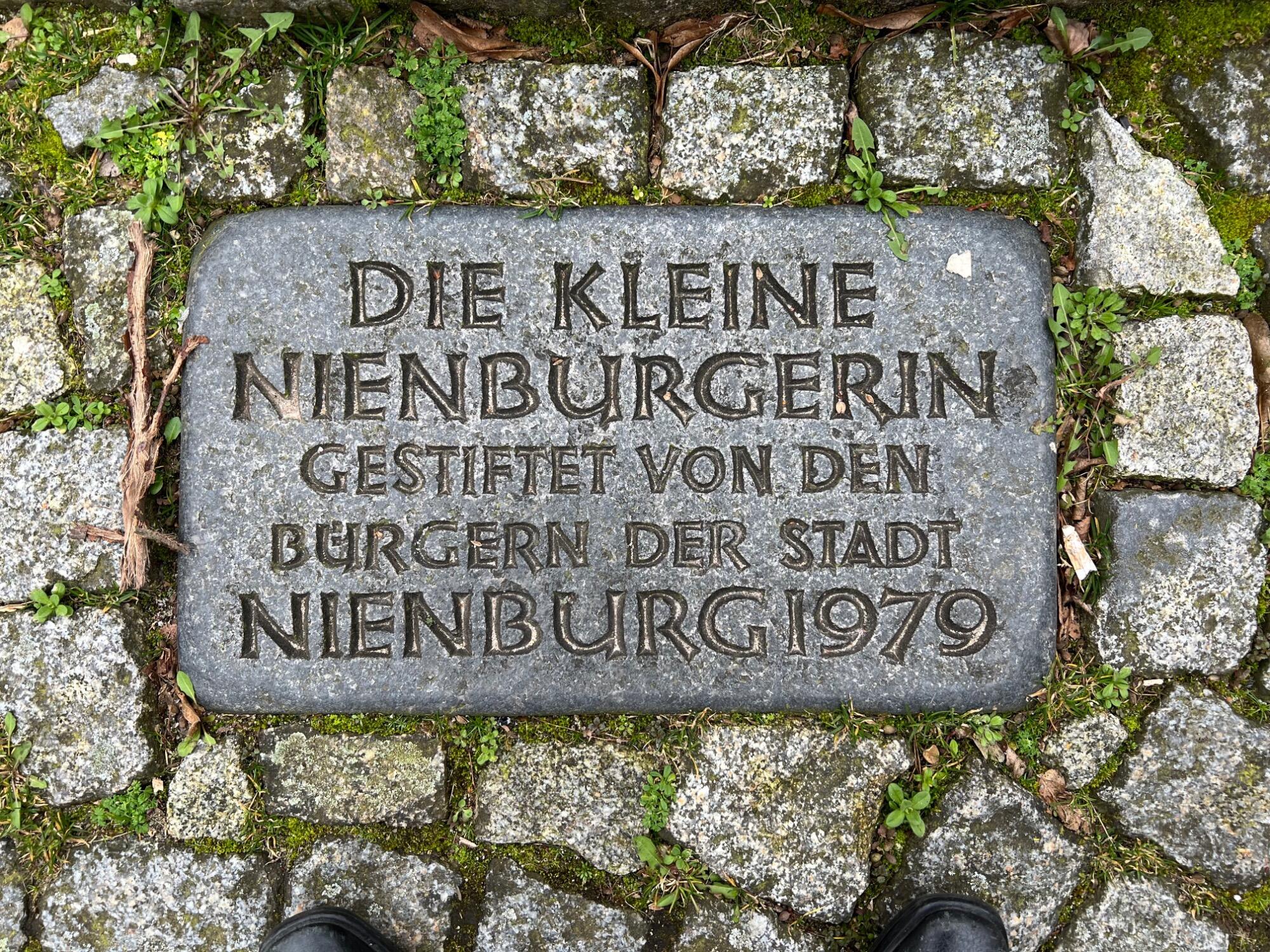
Schriftart ähnlich der Post Antiqua
Das Bild zeigt die Steintafel an einer Skulptur im öffentlichen Raum in Nienburg/Weser. Der Titel der Skulptur lautet "Die kleine Nienburgerin". Die Bildhauerin war Marianne Bleeke-Ehret. Das Entstehungsjahr ist 1979. Das Foto ist von mir, aufgenommen am 4.3.2024. Die Schrift ähnelt der Post Antiqua, jedoch mit auffälligen Unterschieden, wie z.B. das Versal-G und das Versal-U.